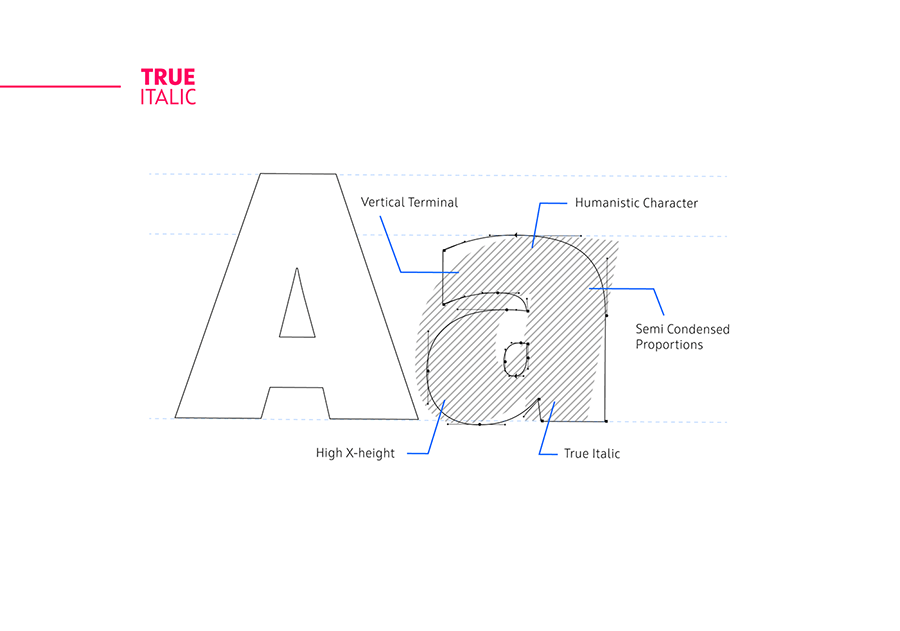
Squad TypeFamily Freedemosquaredis Humanists and Seriew,具有半浓缩的比例。受阿德里安·鲁蒂格(Adrian Rutiger)的独特风格启发,该字体与人类传统风格和当代简约风格协调一致。图中所示为18种黑色字体;封面包括拉丁语、西里尔语和希腊语,涵盖130多种语言;完美的功能并支持多种五种类型功能,如本地化、表格数字、下级和上级、分子和分母、分数、任意连字、区分大小写等。